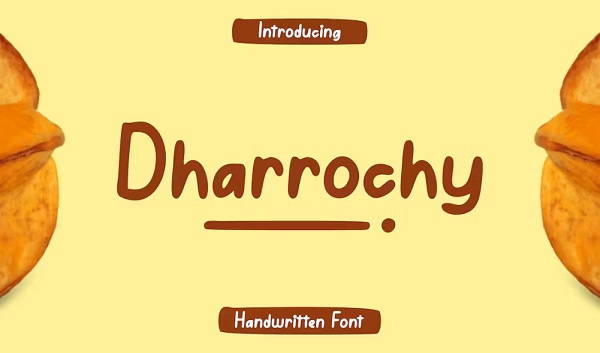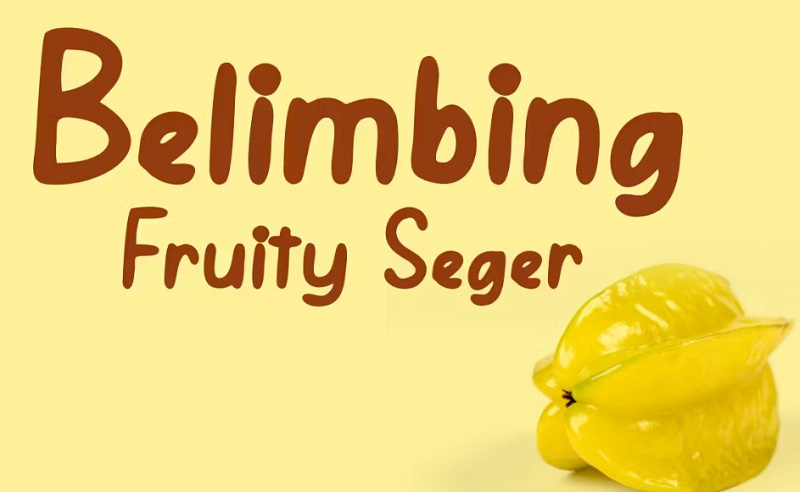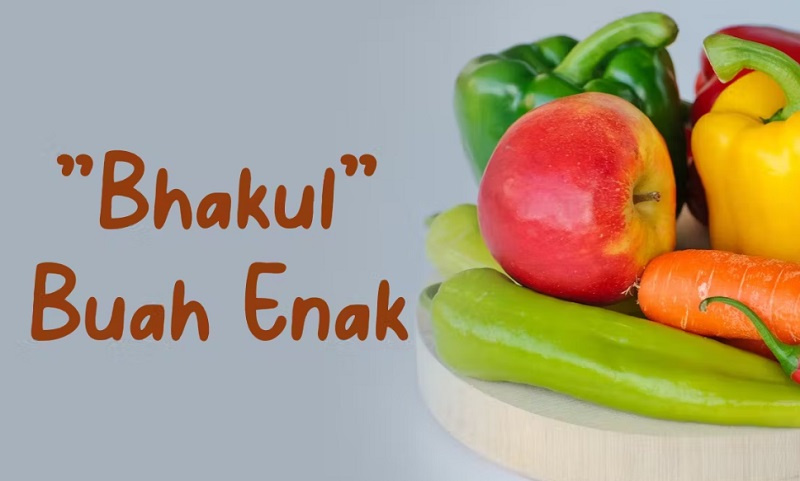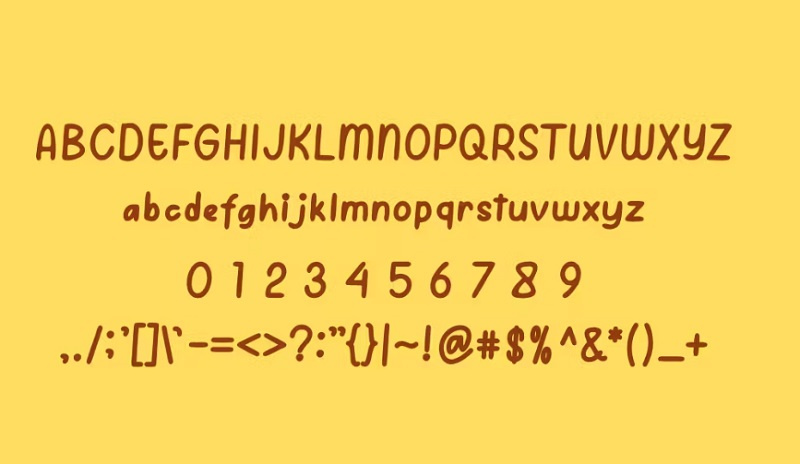
دانلود فونت زیبای انگلیسی Dharrochy
دانلود فونت انگلیسی Dharrochy
دانلود فونت انگلیسی Dharrochy یک فونت مدرن و ساده است. این فونت زیبای انگلیسی به سبک دست نوشته می باشد و مناسب برای انواع پروژه ها و طراحی ها است. مناسب برای لوگو ها، کارت ، طرح بندی مجلات، دعوت نامه ها، سرصفحه ها یا حتی آثار هنری. در رادامه با مشاهده تصاویر پیش نمایش این فونت با ما همراه باشید.
فونت انگلیسی Dharrochy